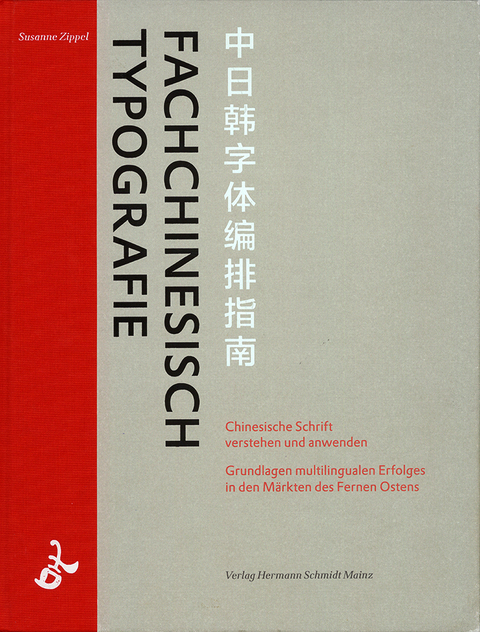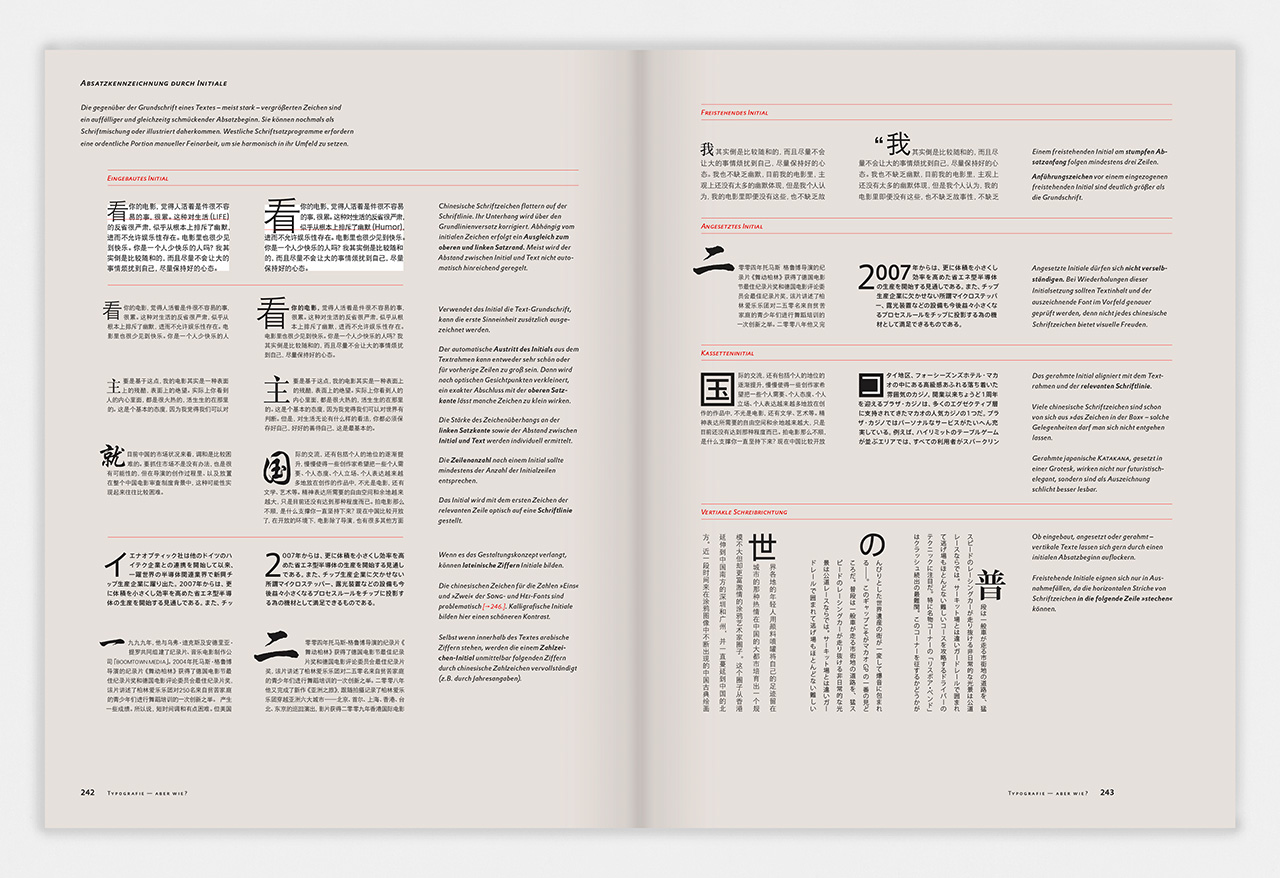
Fachchinesisch Typografie
Chinesische Schrift verstehen und anwenden. Grundlagen multilingualen Erfolges in den Märkten des Fernen Ostens.
Das Epizentrum der Wirtschaft hat sich verlagert: Fernost gibt den Ton an und den Takt vor. Das heißt für Kreative, die Chancen suchen: Go east! Wie aber gestaltet man in einer Sprache, die man nicht versteht und deren unendlich viele Satzzeichen man nicht kennt? Wie findet man den Einstieg in die CJK-Typografie?Susanne Zippel ist in beiden Welten zu Hause. Ihre Agentur hat sich auf visuelle Gestaltung und Branding für westliche Unternehmen für die fernöstlichen Märkte spezialisiert. Mit preußischer Akribie und chinesischen Netzwerk-Kompetenzen hat sie etwas zustande gebracht, worum uns die Chinesen beneiden:Fachchinesisch, eine Detailtypografie für die Märkte in China, Japan und Korea.Ein Buch, das Ihnen die nötigen Grundlagen praxisnah vermittelt und Ihnen den Zugang zu den jeweils zehntausenden Zeichen einzelner CJK-Fonts erschließt. Sie brauchen nicht Chinesisch lernen, um multilinguale Dokumente erstellen zu können, aber Sie brauchen einen verlässlichen Begleiter, ein Buch mitSatzregeln zur Gestaltung mit chinesischer Schrift,Regeln zum Umgang mit Laufweiten, Absätzen, Umbruch, Registerhaltigkeit, Initialen, Auszeichnungen, Satzzeichen, Interpunktion ...,Tipps zum Vom Einsatz westlicher Textprogramme,Mischen von lateinischer und chinesischer Schrift,Typo-Checkliste und Tipps zum Anlegen für bilingual Dokumente und Tipps zum Anlegen von Dokumenten,umfangreichem Typografie-WörterbuchWenn Sie mit erfolgreichen Auftraggebern weiter im Geschäft bleiben wollen, werden Sie früher oder später nicht umhin kommen, sich mit CJK-Typografie zu beschäftigen - und wenn Sie es anhand dieses Buches tun, wird die Auseinandersetzung mit einem faszinierenden Schriftsystem zu einem typografischen Abenteuerurlaub der Extraklasse!